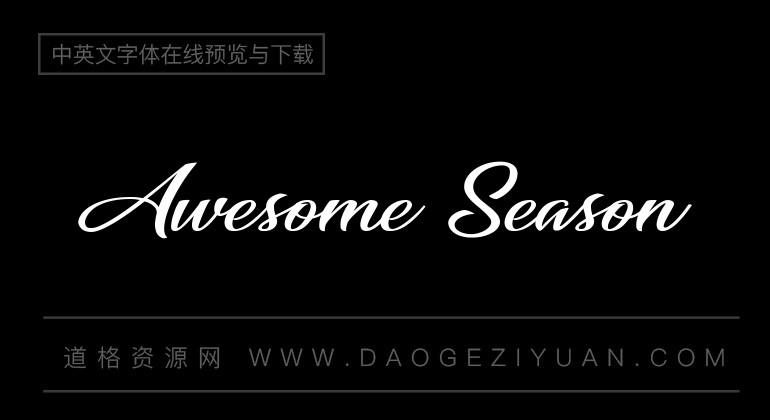
Awesome Season 是一款由 Xerographer Fonts 设计的免费字体。它是一种手写风格的字体,具有非常自然且轻松的感觉。字母的线条流畅,有一定的波动,让人感觉仿佛是用毛笔或钢笔书写的一样。这种字体的特点是非常适合用于节日、季节或其他具有欢乐气氛的场合,比如制作卡片、海报、招贴等。Awesome Season 字体包括大写和小写字母、数字、标点符号等,非常适合需要添加一些个性化元素的设计项目。内容介绍
Awesome Season是一款非常不错的手写艺术字体,具有很好的视觉感,适合于文化类的宣传设计、商业类品牌的广告和产品包装设计以及个性化文字排版等较多场景。